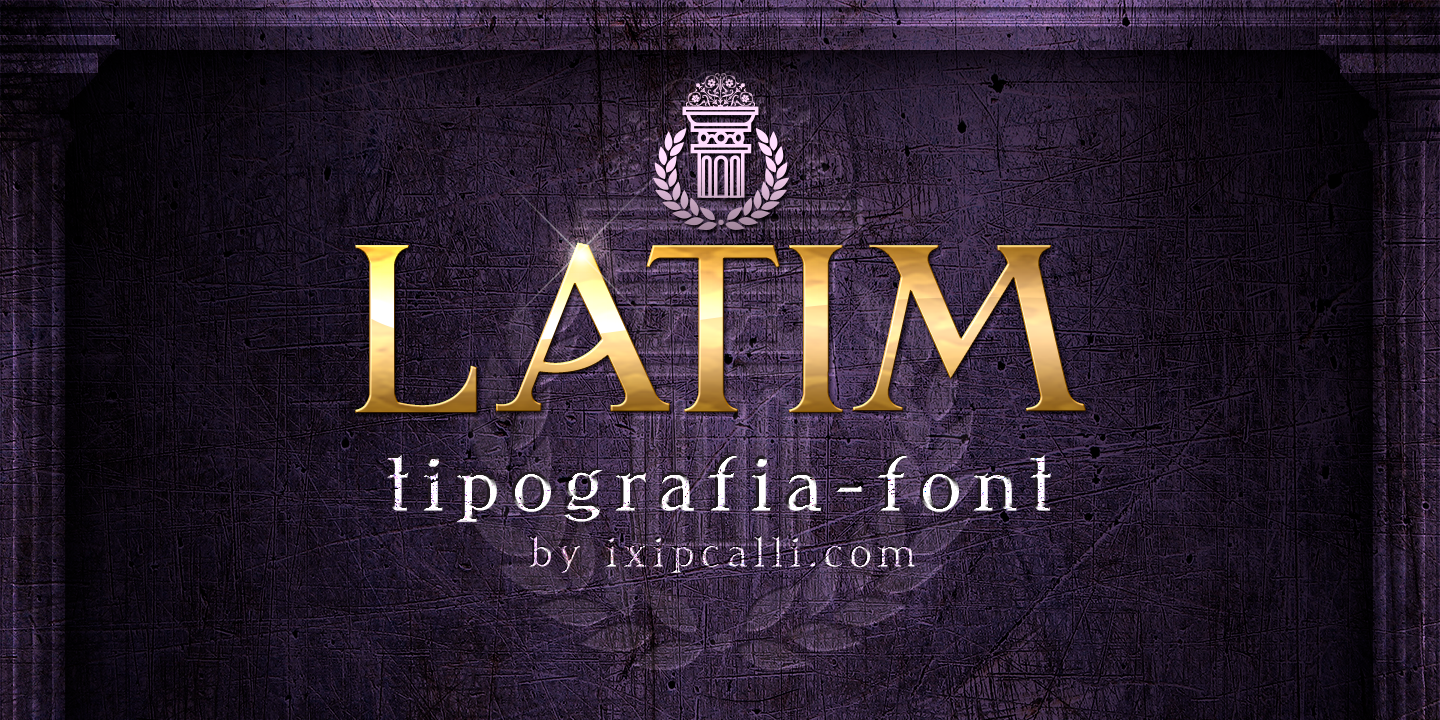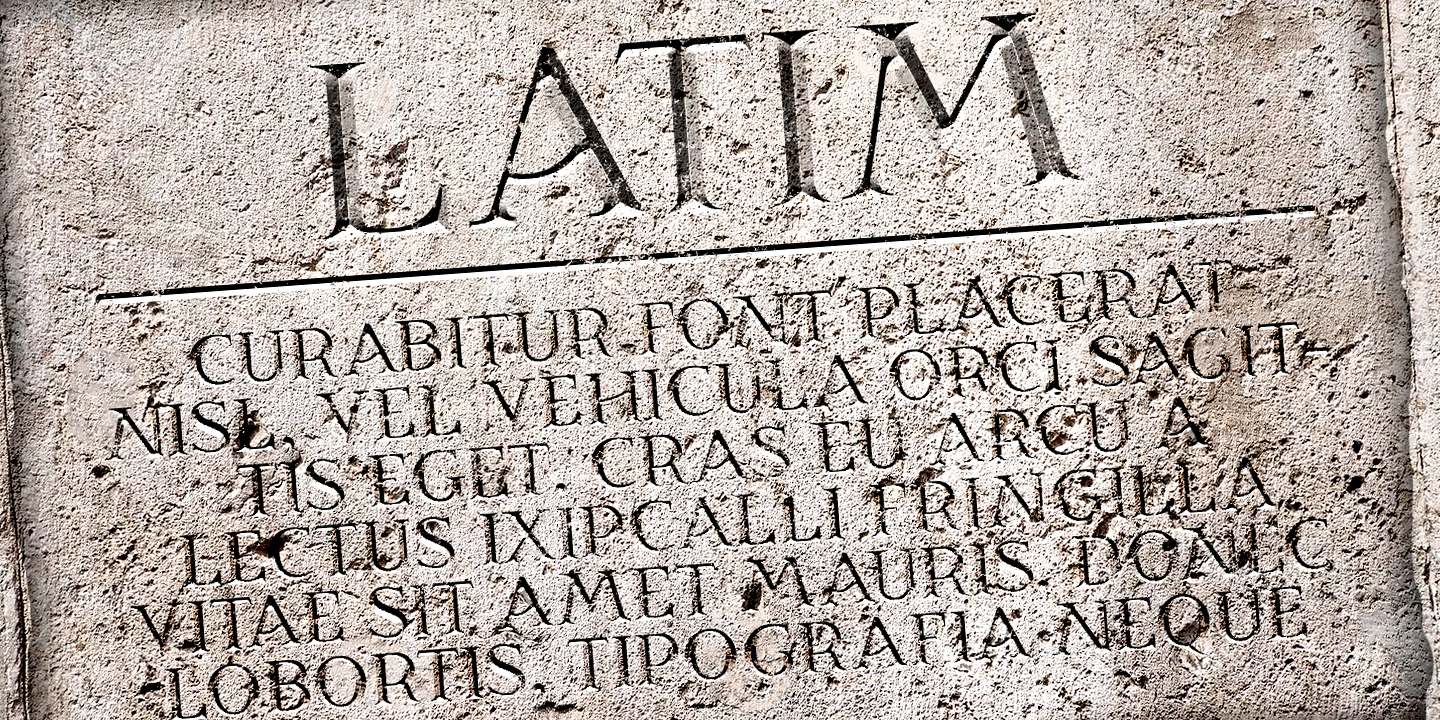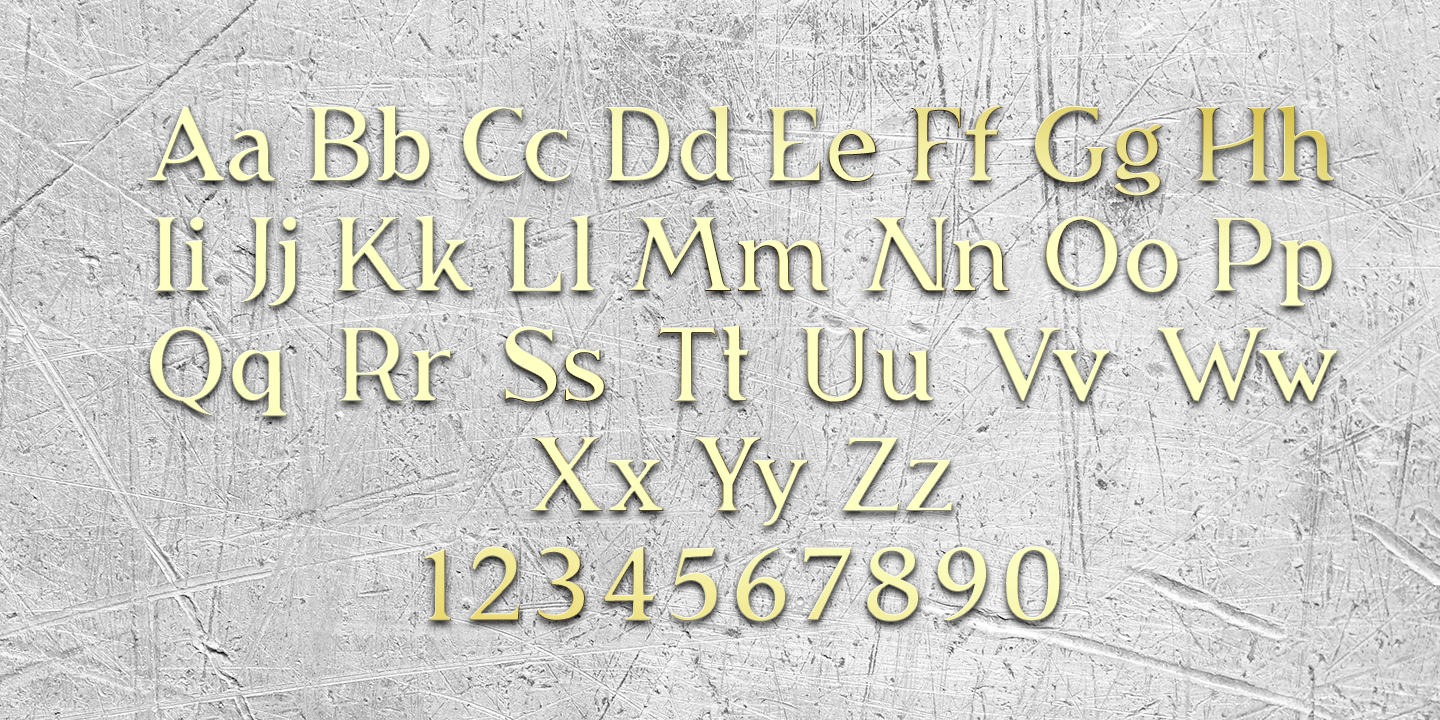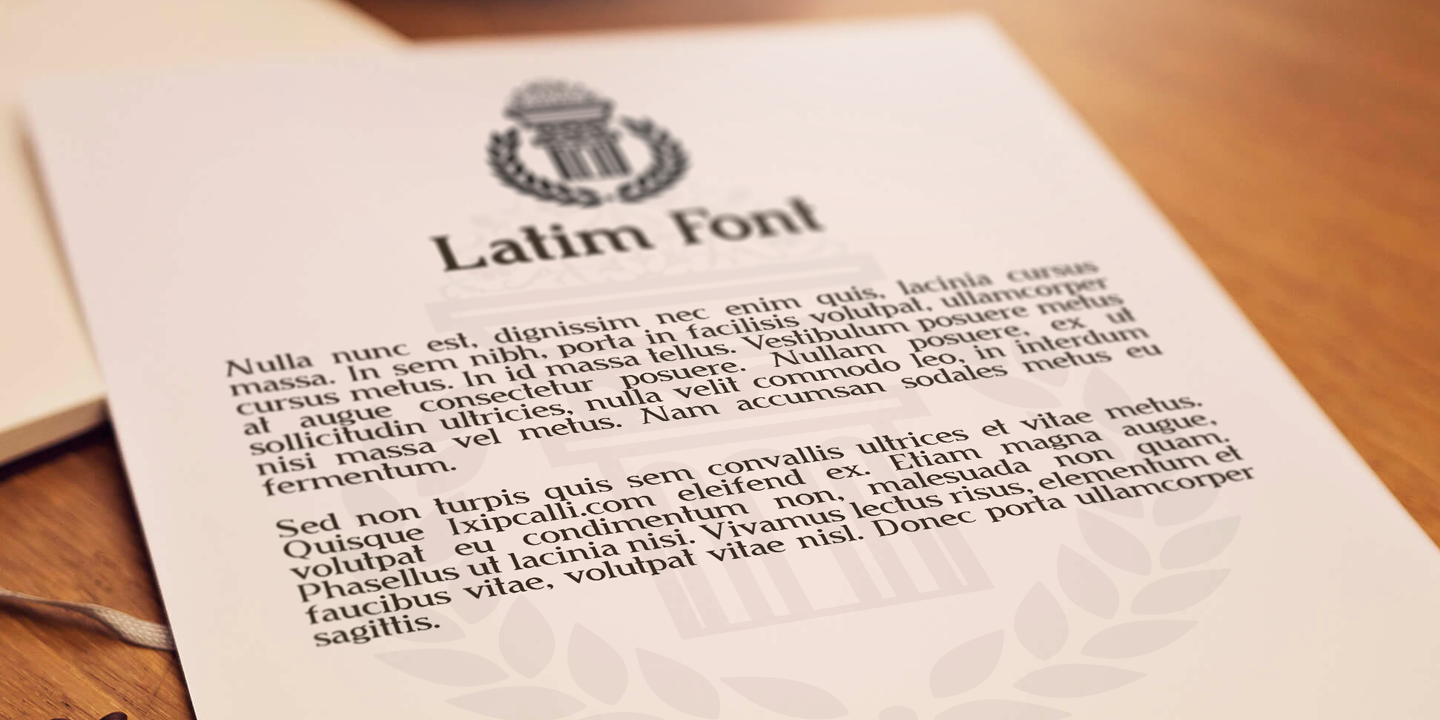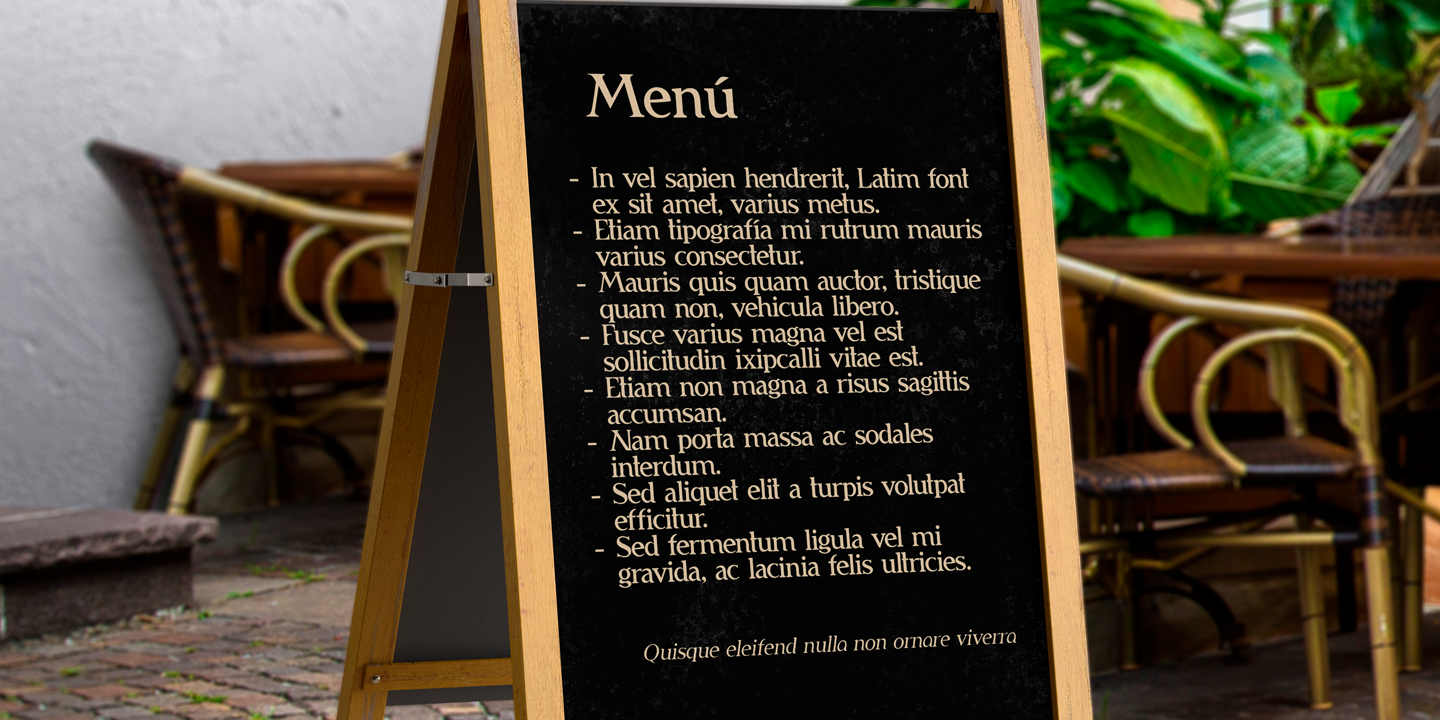
Latim es una tipografia inspirada en el esitlo románico latino
La fuente amplía su uso proporcionando 4 pesos desde delgado hasta negrita; mientras que los pesos más delgados han reducido el contraste y las correcciones ópticas para crear una apariencia cálida y suave. Los tamaños de letra grandes, puede apreciar las formas de las letras, mientras que la misma moderación y enfoque crean una textura uniforme para tamaños de letra pequeños y lectura larga.
Latim is a typeface inspired by the Latin Romanesque style
The font expands its use by providing 4 weights from thin to bold; while thinner weights have reduced contrast and optical corrections to create a warm, soft look. Large font sizes, you can appreciate the shapes of the letters, while the same restraint and focus create an even texture for small font sizes and long reading.